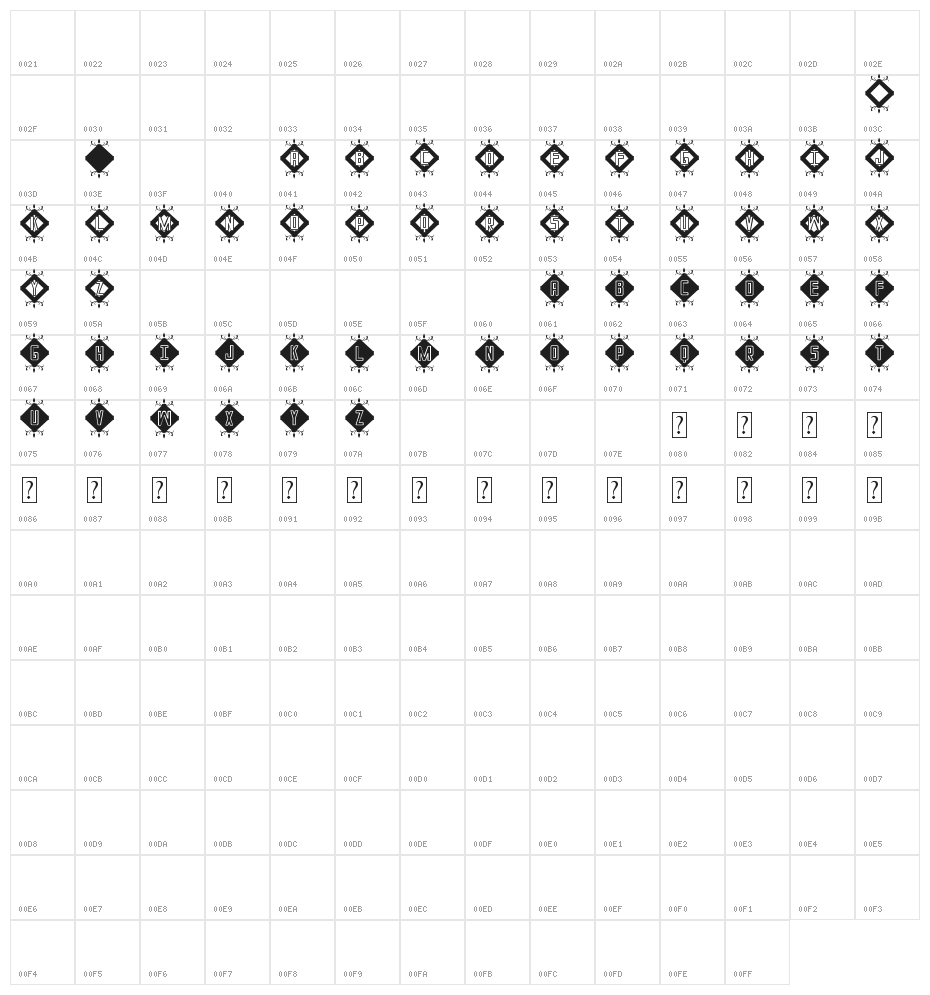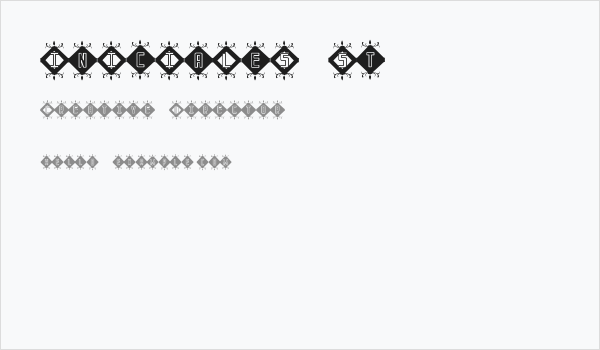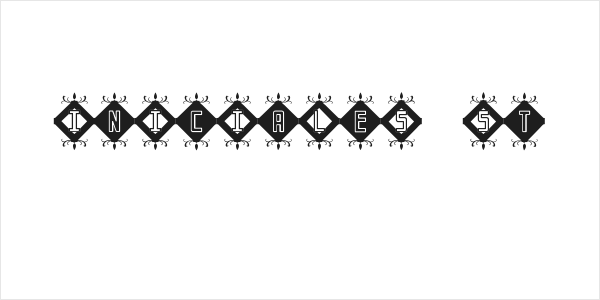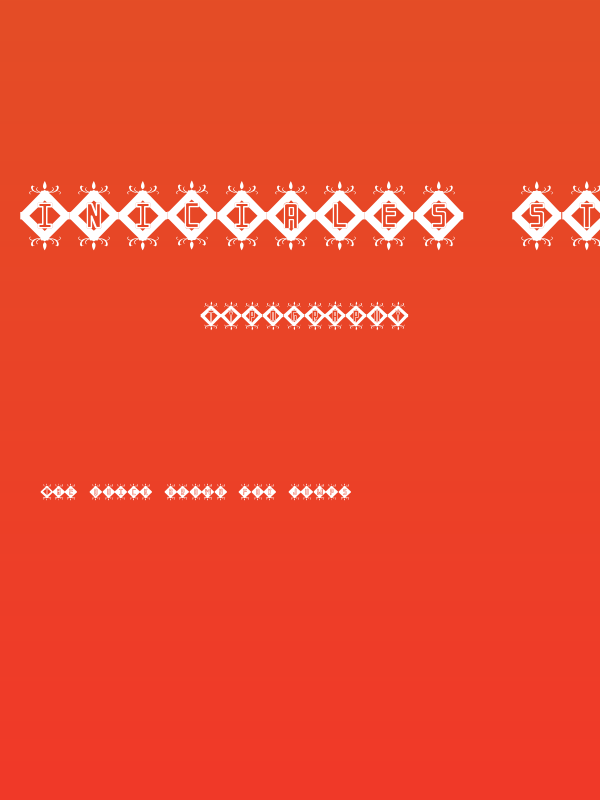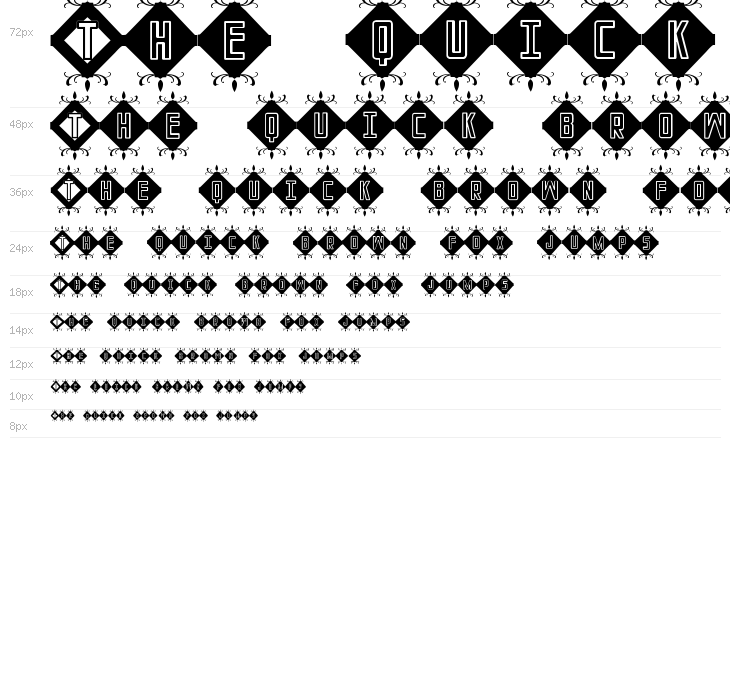
InIcIaLeS St Font
| Anwendungsfall | Logos, Posters, Invitations |
| Vorgeschlagene Projekte | Ideal for creative projects such as logos, posters, and invitations where a unique and artistic touch is desired. |